特別な瞬間を紡ぐ文字「金花体」で伝えたい、大切な人への言葉を大募集! ダイナフォント2022年カレンダー「色詩暦 季節を詠む」を抽選で50名にプレゼント
ダイナコムウェアは、特別な瞬間をさらに輝かせるダイナフォント2021年新書体「金花体」で伝えたい、大切な人への言葉を2021年11月25日(木)~12月5日(日)までの期間、募集している。
また、参加した人の中から抽選で50名に、12の暦を表現したイラストと詩をそれに適した書体で表現したダイナフォント2022年カレンダー「色詩暦(いろうたごよみ) 季節を詠む」がプレゼントされる。
ダイナフォント2022年カレンダー「色詩暦 季節を詠む」
ダイナコムウェアでは例年ダイナフォントを使用したオリジナルカレンダーを制作している。
ダイナフォント2022年カレンダー「色詩暦(いろうたごよみ) 季節を詠む」は、春夏秋冬それぞれの12の暦の情景を描いたイラストと詩、また、それに適した書体で美しく表現したカレンダーとなる。
また、デザイン面だけでなく機能面も考慮に入れ、記入スペースの確保や当月の前後1ヶ月、六曜も表記。
文字の美しさや文字文化の素晴らしさに触れたカレンダーで、ぜひ、2022年365日の毎日を過ごそう!
特別な瞬間を紡ぐ文字「金花体」で伝えたい、大切な人への言葉を募集
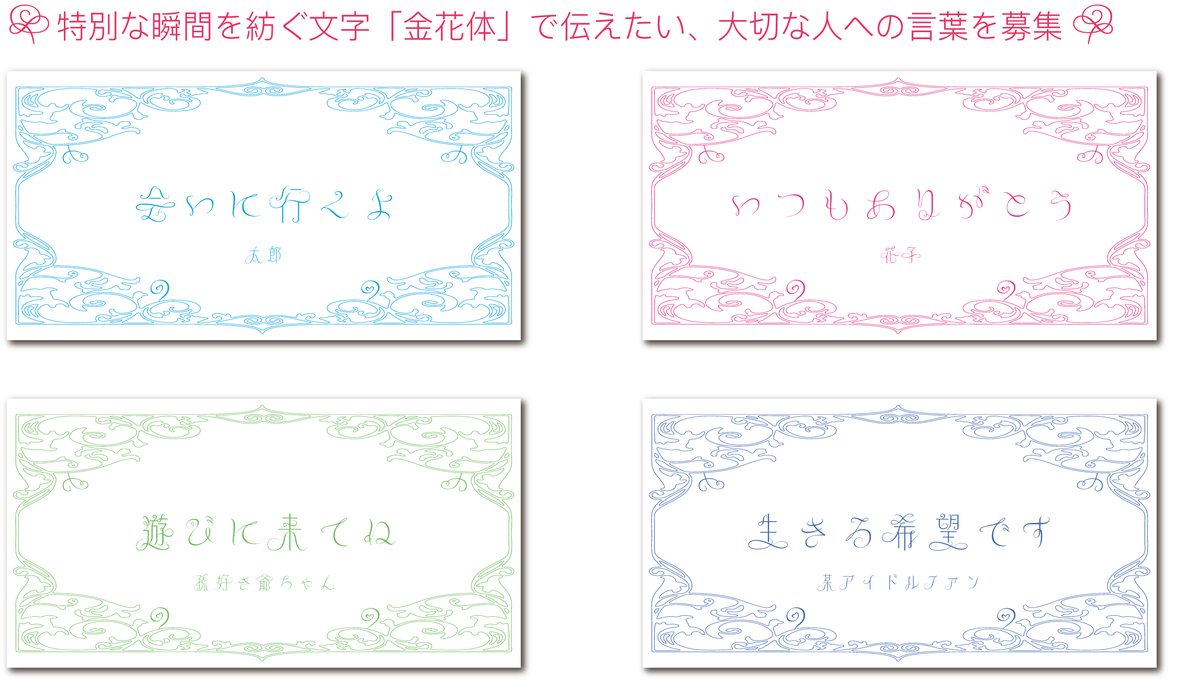
「金花体」で伝えたい、大切な人への言葉を募集するキャンペーンとなる。
ダイナフォント2022年カレンダーの当選者には、金花体で表現した言葉をグリーティングカード画像も応募したメールアドレスに送られる。
ダイナフォント2021年新書体「金花体」
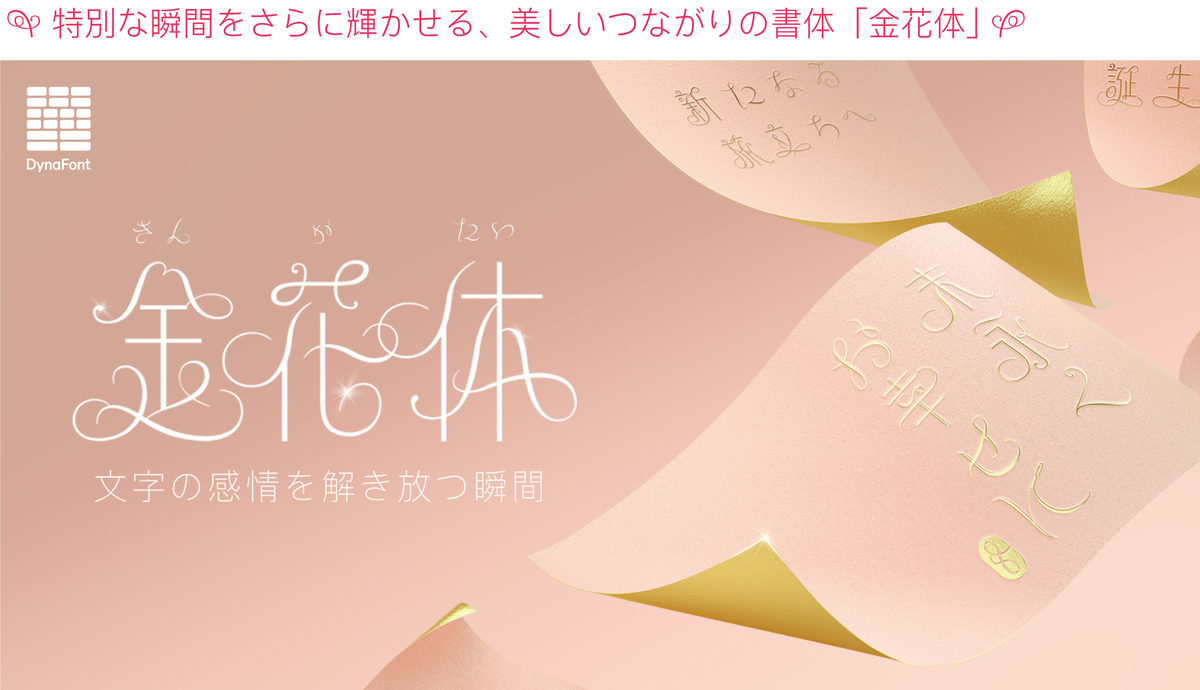
特別な瞬間をさらに輝かせる、美しいつながりの書体「金花体」
「金花体」は、金文の縦長の字形に中国戦国時代の青銅器「中山王方壺」の蟠龍の彫刻をカリグラフィーの流れるような曲線美で外側に伸ばすというこれまでのデザインの常識を取り払った稀有な書体。
「金花体」の特長である一筆書きのように文字を続けて書く手書き文字の筆記体は、これまで欧文特有のデザインということもあり、漢字や仮名のデザインに取り入れる試みは正に革新的といえるだろう。
さらに「金花体」には、カリグラフィーのエレメントから作成した装飾を文字セットから選んで自由に組み合わせることが可能になるなど、これまで類を見ない書体になっている。